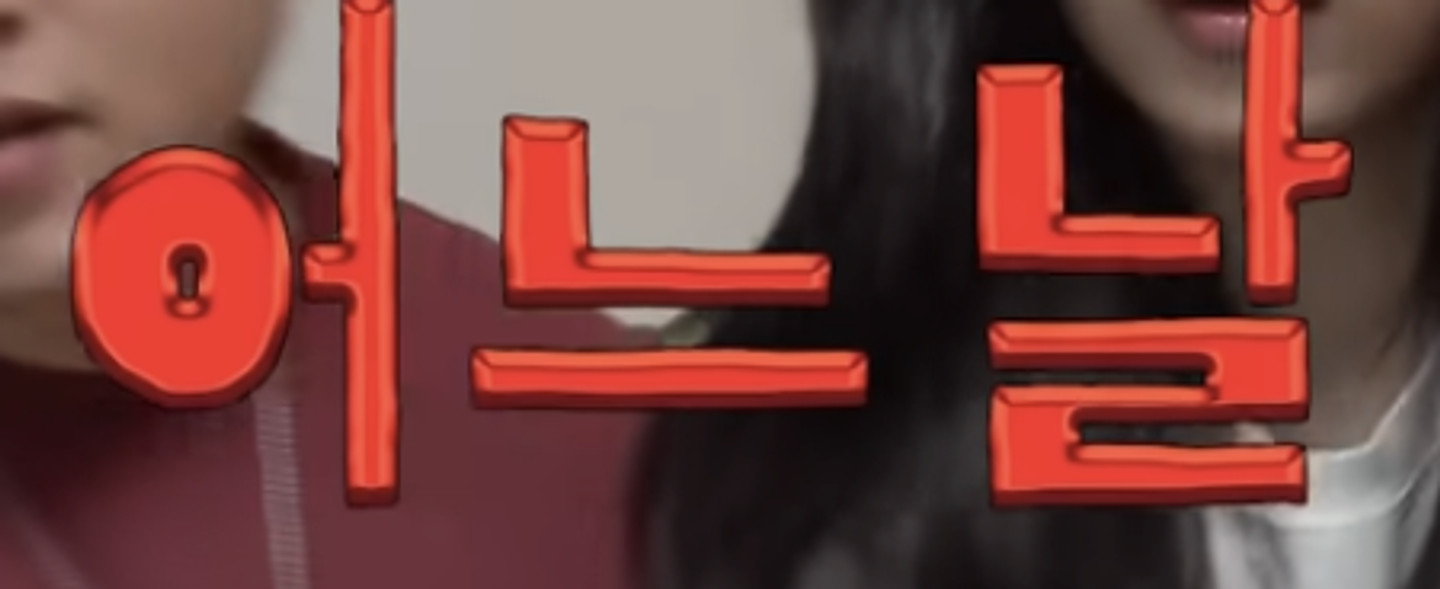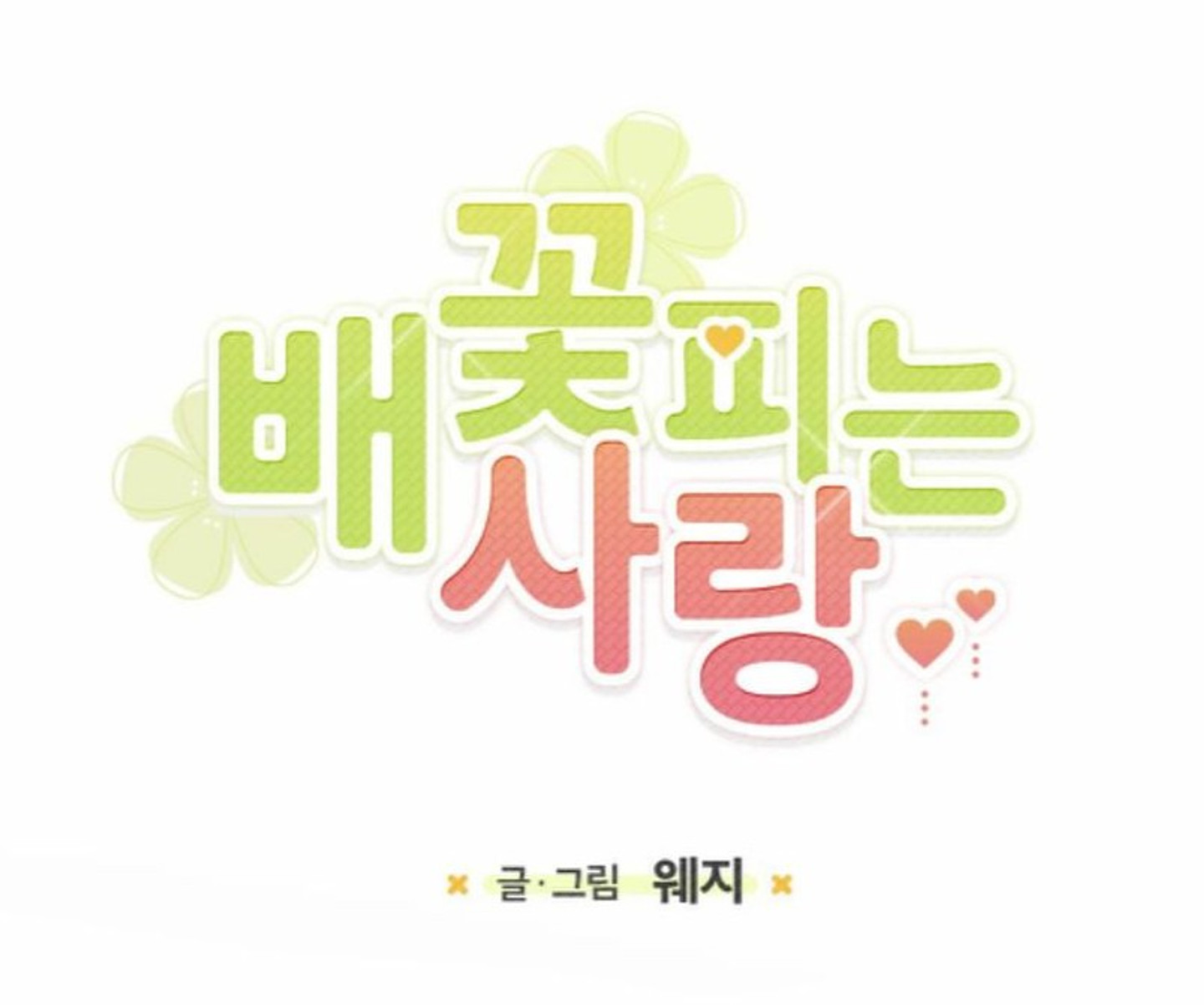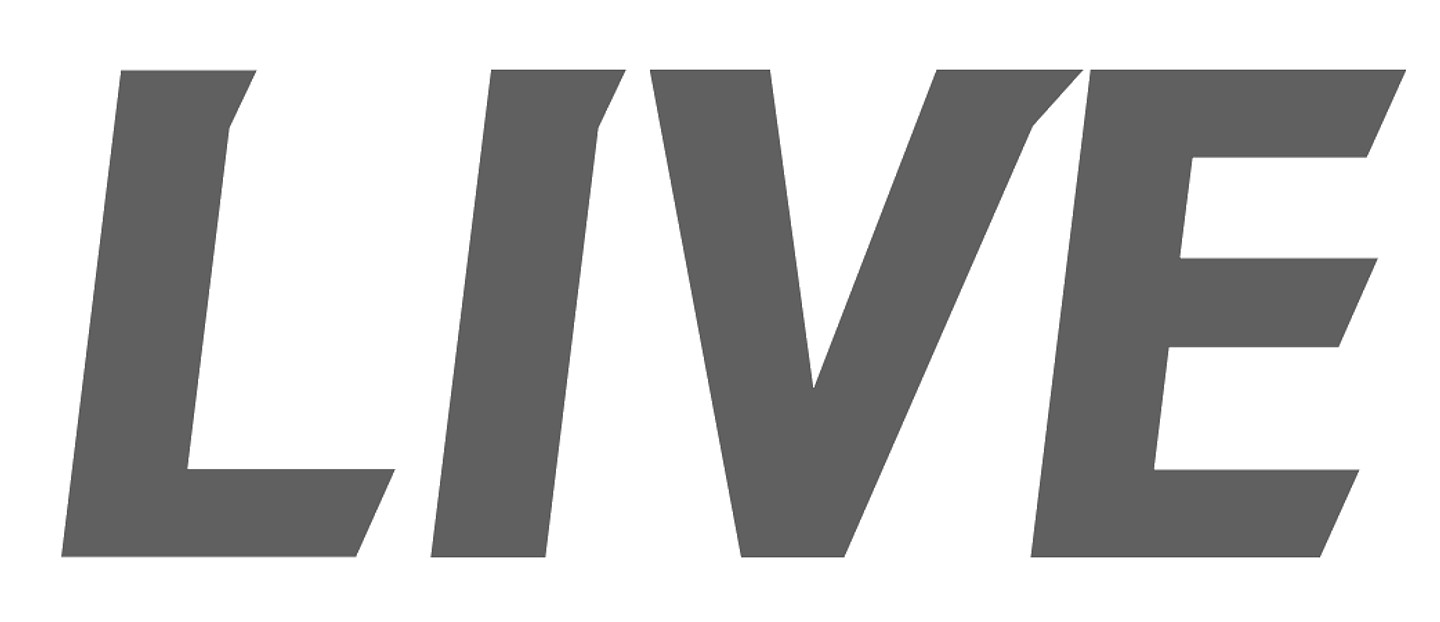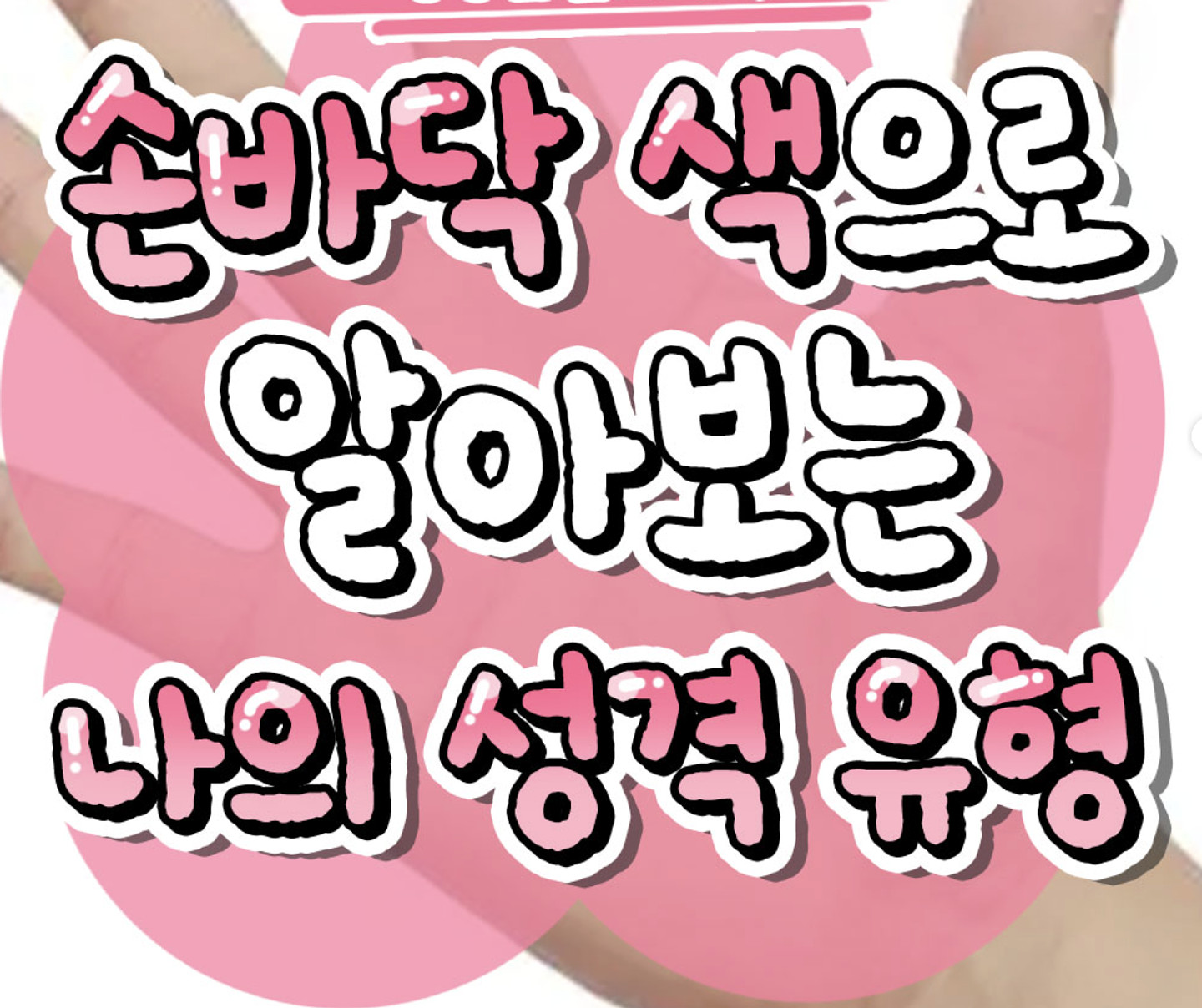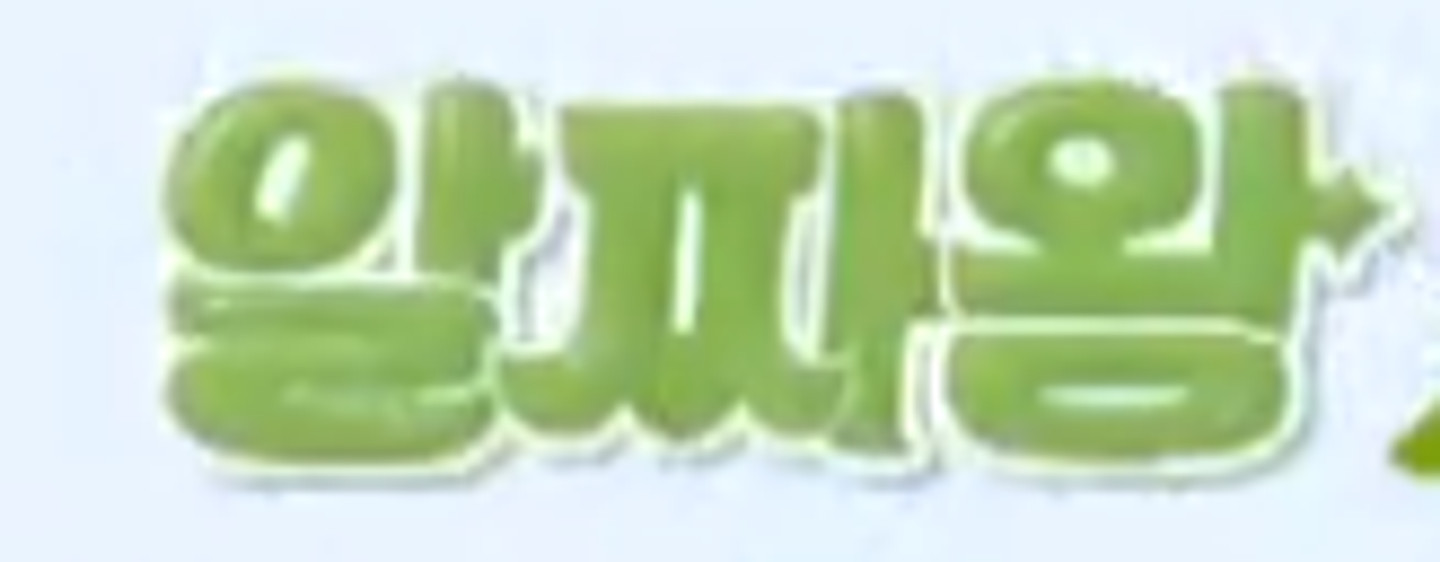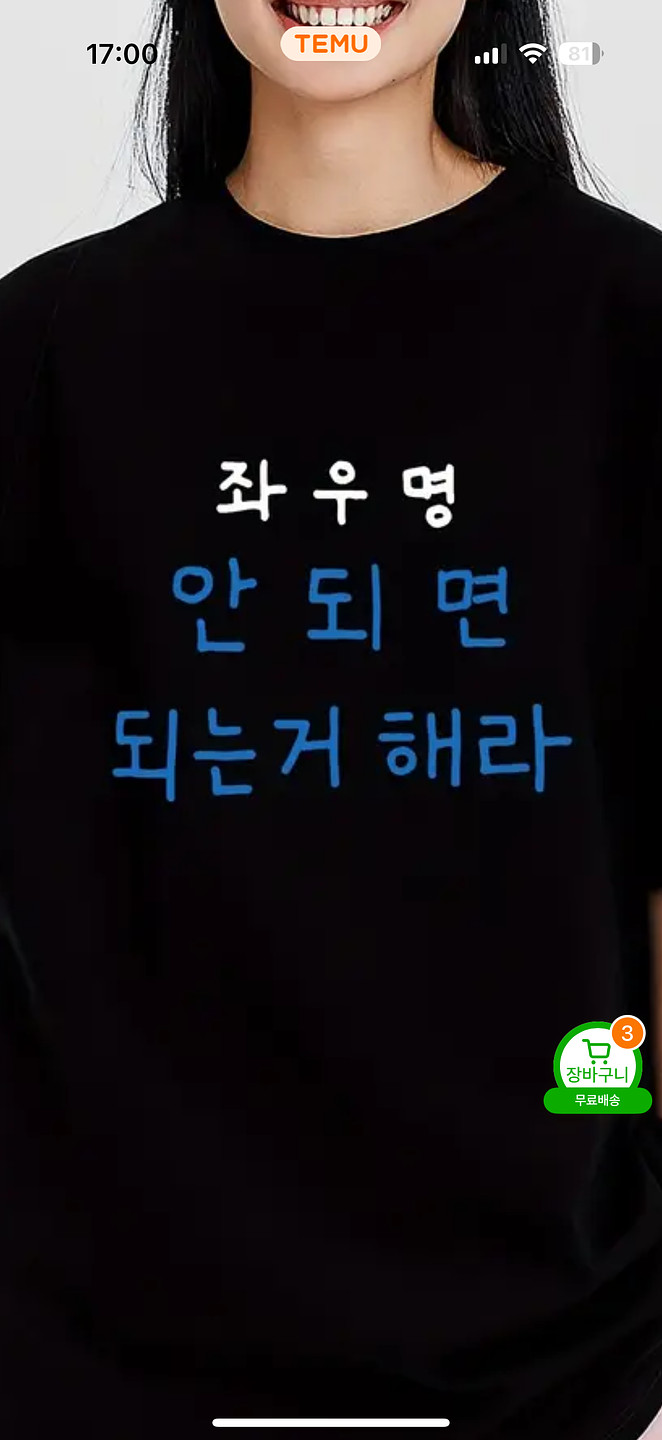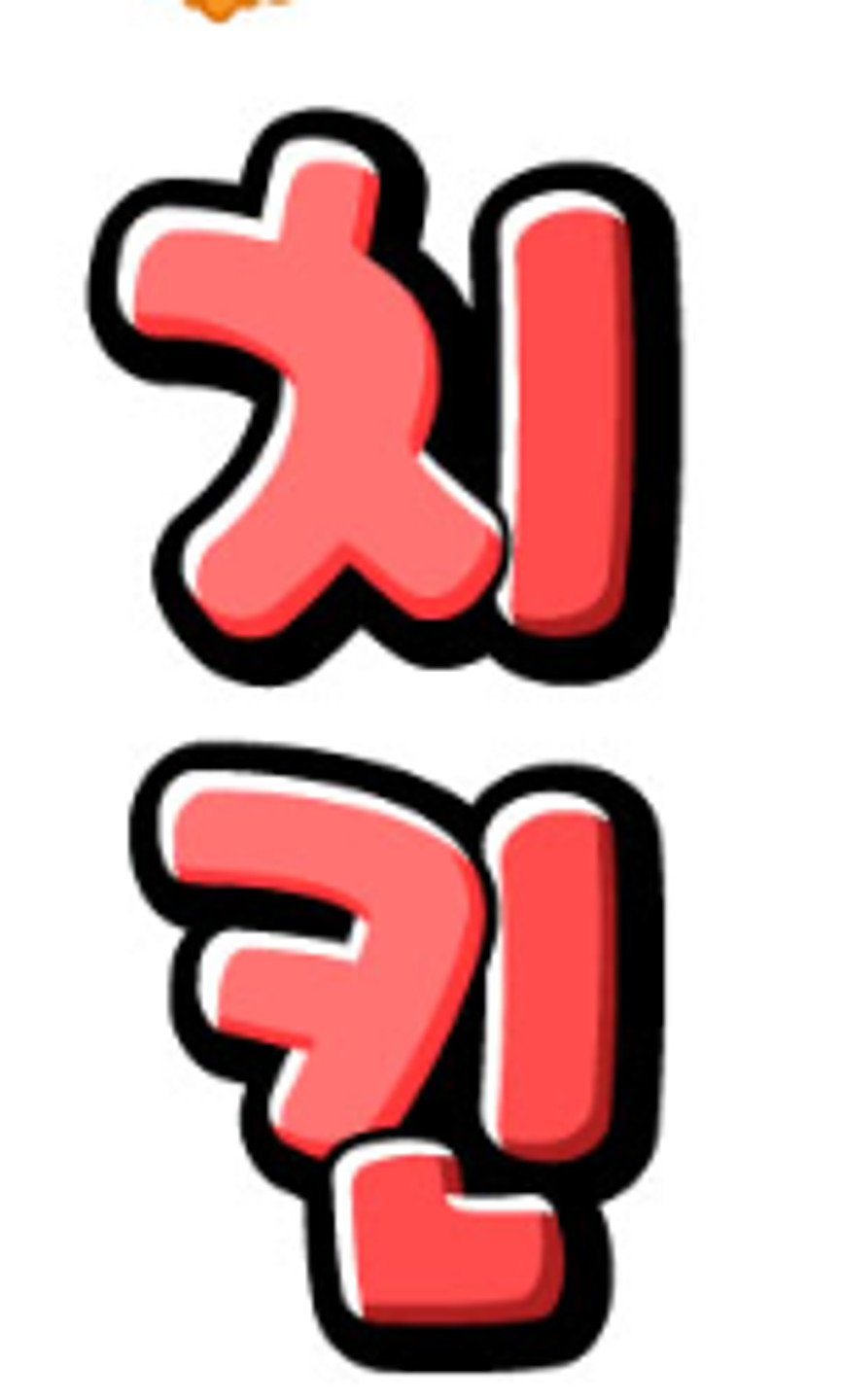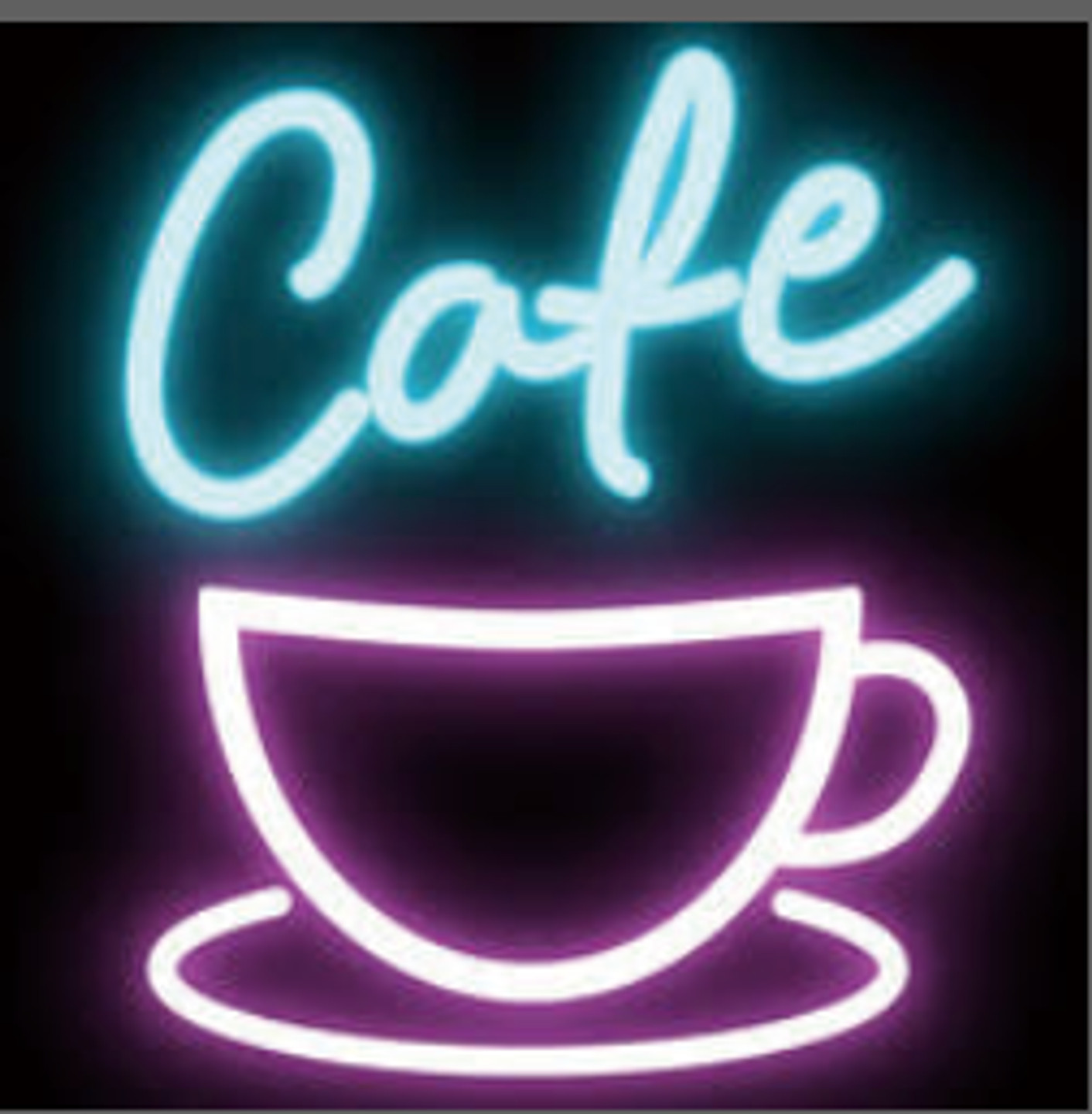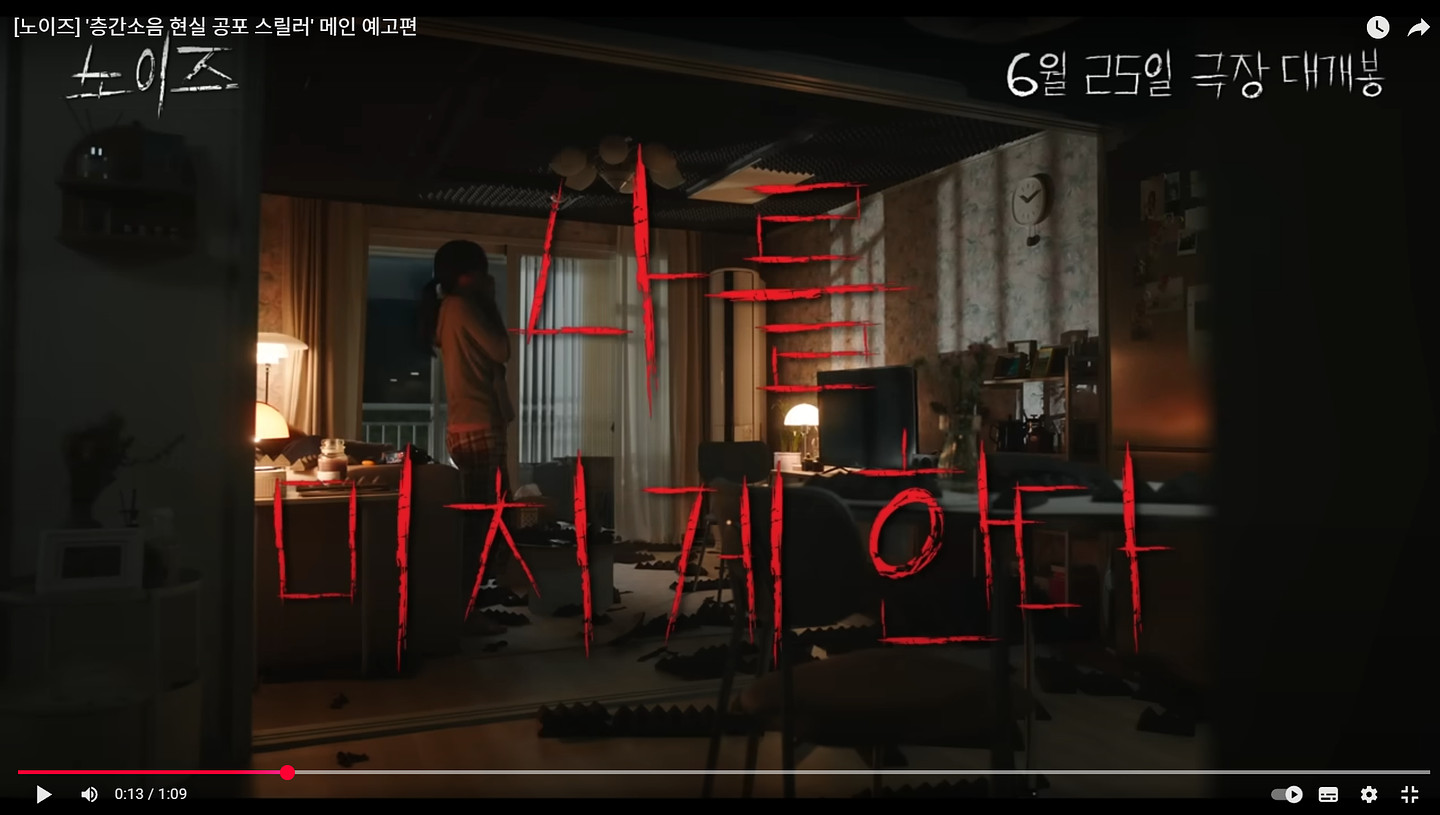
무슨 폰트일까요..! 부탁드립니다..!
무슨폰트일까요 ㅠ
우측에 있는 영문 폰트가 ㄱ ㅇ금힎
테마 다운 받다가 블로그 주인장님이 쓰시는 폰트 궁금해서 여기 올려보아요 ㅠㅠ 무슨 폰트일까요.. ㅠㅠ
혜안님 유튜브에 나오는 폰트입니다!
이 폰트 뭘까요 도와주세요
이 폰트랑 최대한 비슷하ㄴ거 찾아주세요 제발 빨리 부탁드릴게요 제발데제발
무슨 폰트 일까요?!
이고 폰트 몬가요 ???!
폰트궁금해요
예능 <나라는 가수> 프로그램 소향이 부르는 <사랑의 찬가> 영상에 나온 폰트입니다.
이폰트 뭘까요 ㅠㅠ!!
이 폰트 너무 궁금해요 ㅠㅠ
이거 정보 급해요 ㅠㅠㅠㅠㅠ
손글씨 글씨체인데 잘 찾기 어려워서요...
얼마나 억눌려 살았는지 보여줌 무슨 폰트인가요?
이런 장꾸 느낌 나는 폰트 아시는 분 계실까요ㅜㅜㅜ 도와주세오ㅠㅠ
무슨 폰트일까용..
웹툰 소스 사이트에서 샘플로 올라온 이미지에서 발췌했습니다! 그래서 제목도 모르고 작가님도 몰라요ㅠ 무슨 폰트인지 알 수 있을까요?
첫줄 둘째줄 각각 폰트 이름 뭘까요ㅜㅜ
인스타 보다가 이쁜 폰트를 보게 되었는데 궁금합니다
어비 폰트 중에 뭔가요ㅠㅠ
무슨 글씨체일까요 ㅜ.ㅜ
이 폰트 너무 궁금해요🥹🥹
이거 뭘까요?!
폰트찾기 이슈
이 폰트 유튜브에서 많이 보이던데 도저히 못 찾겠어요..ㅜ
이거 폰트 뭔지 알고싶습니다!!
일본어 폰트인데 어떤 폰트인지 모르겠어요 아시는 분 계실까요 ..?
뉴닉에서 자주 사용하는 폰트같은데 어떤걸까요..?
유튜버 하네님 브이로그에 나오는 폰트 너무 궁금합니다!!!!!! 폰트 고수분들 도와주십셔..
인스타 드라마짤에서 본 폰트 궁금해서 문의 드립니다.
글씨 예쁘네요 궁금합니다
폰트 뭐예요...?
이거 폰트 뭔가요? 출처: 유튜브 안가뇽
이 글씨체는 뭘까요?
휴대폰 폰트인데 너무 궁금해요
영상속 자막 "아직도 해 드릴 게 참 많은걸요" 글자체 궁금해요
이런 폰트 없나요..? 8비트 폰트라기엔 좀 다른거같아서요..
이거 무슨 폰트인가요 유료면 비슷한 길쭉길쭉한 폰트라도 없을까요..?
90년대 느낌 폰트 꼭 찾고싶어요!!
이 폰트 아시는 분 계신가요..?
어떤 폰트인지 아시는 분.. ㅜㅜ
이 폰트는 어떤폰트일가요
친근하고 귀여운 손글씨 스타일: 정돈된 디지털 폰트보다는 사람이 손으로 직접 쓴 듯한 자연스럽고 따뜻한 느낌을 주는 서체입니다. 둥근 모서리 처리: 거의 모든 획의 끝부분이 각지지 않고 부드럽게 둥글게 처리되어 있어 전체적으로 유하고 다정해 보입니다. 일정한 굵기: 각 글자를 구성하는 획의 굵기가 대부분 일정하며, 굵은 붓펜이나 두꺼운 사인펜으로 쓴 듯한 안정감을 줍니다. 높은 가독성: 손글씨 스타일임에도 불구하고 각 자음과 모음의 형태가 뚜렷하게 구분되어 있어 읽기가 매우 쉽습니다.